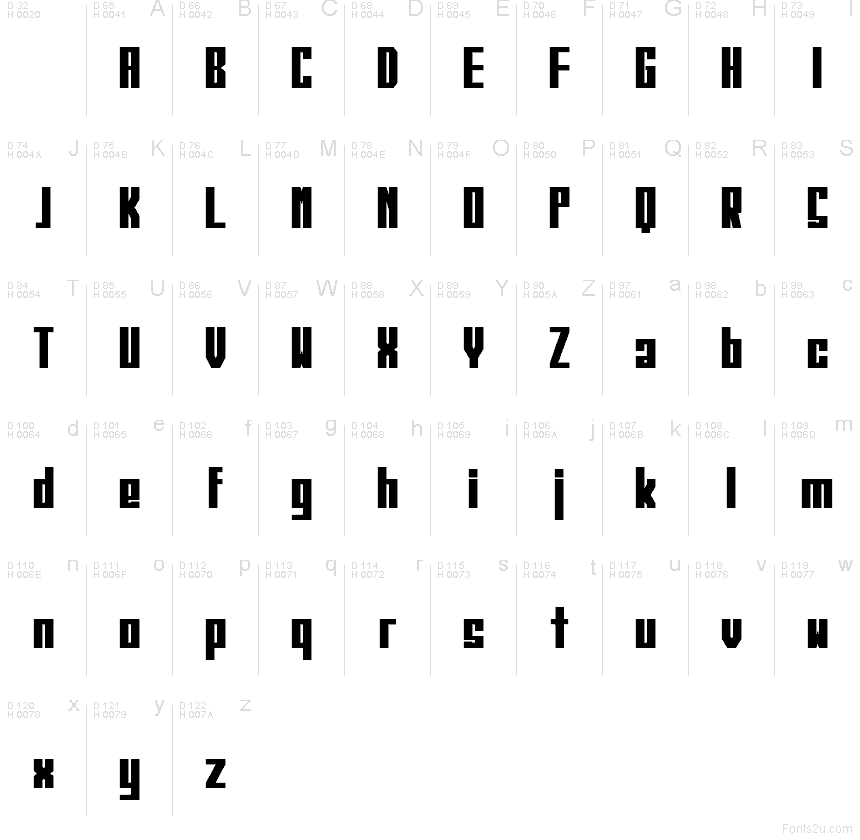
Vanishing Ultra Condensed od Vladimira Nikoliće je bezplatné bezpatkové písmo typu display, které definují vysoké, úzké siluety a náhlé chybějící části, díky nimž litery působí jako vyseknuté. Opakující se mezery ve tvarech vytvářejí trhaný rytmus, který písmu dává výraznou plakátovou přítomnost namísto hladkého a plynulého toku.
Zúžený vertikální tvar propůjčuje krátkým titulkům silný charakter na hudebních letácích, v názvech her, na filmových plakátech, v eventové grafice i streetwearových designech. Tyto ostré obdélníkové výřezy se skvěle hodí také pro obaly alb a loga, kde hrubší, přerušovaná textura pomáhá textu působit napjatě, městsky a záměrně neúplně.
Vanishing Ultra Condensed